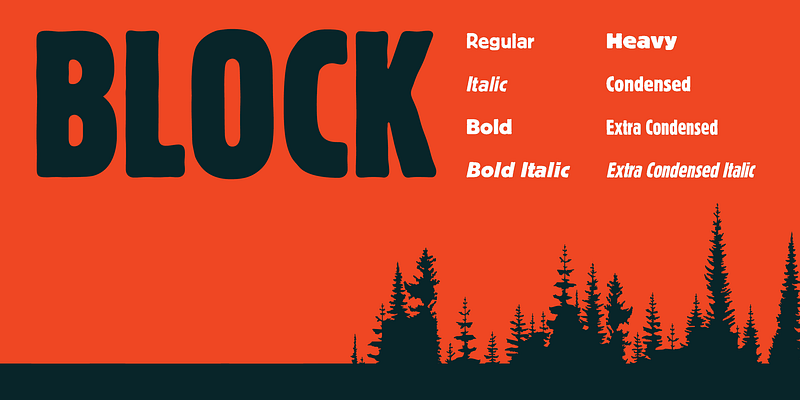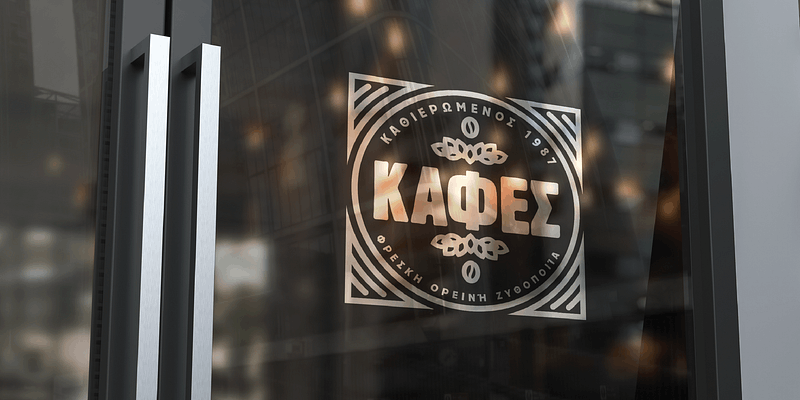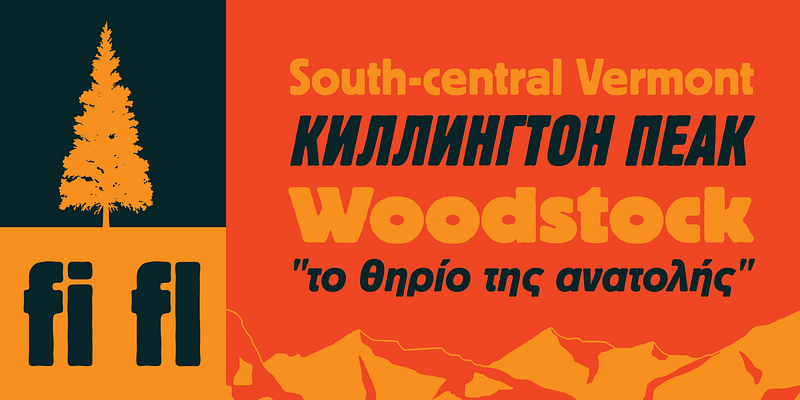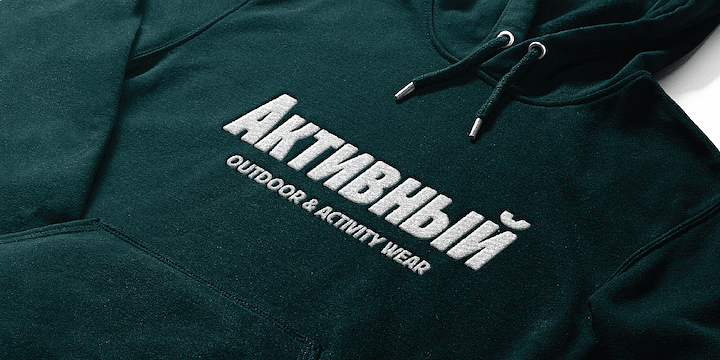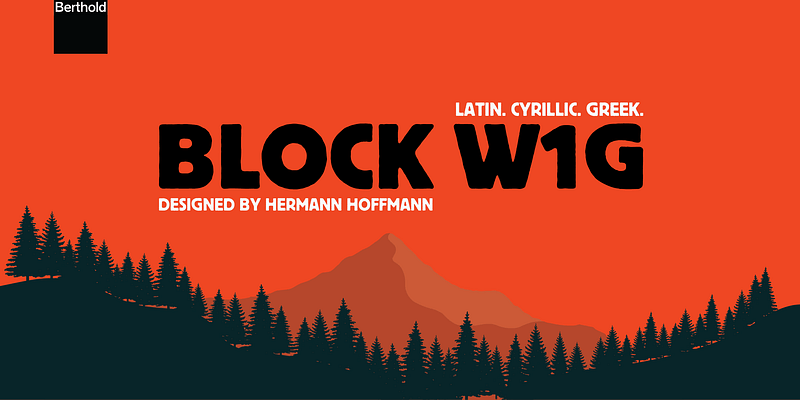
H. Hoffman이 디자인한 H. Berthold는 1908년에 Block을 처음 출시했으며, 이후 Hoffman이 1926년까지 재작업한 후속 버전을 출시했습니다. 독특한 굵은 글자와 매우 짧은 디센더가 특징인 Block은 수십 년 동안 독일에서 활자 인쇄의 필수 요소였습니다. 1970년대 후반에 H. Berthold는 이탤릭체를 포함한 두께를 추가하여 더 많은 유연성을 제공했습니다.